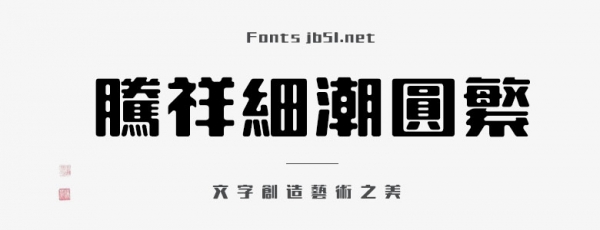
騰祥細(xì)潮圓繁體是一款不錯(cuò)的藝術(shù)字體,由騰祥字庫(kù)出品,字體是在細(xì)潮黑基礎(chǔ)上變換設(shè)計(jì)而成。細(xì)潮圓將細(xì)潮黑的棱角柔化形成被融化之感,融化了的筆畫(huà)圓潤(rùn)富于親和力,適合應(yīng)用于藝術(shù)設(shè)計(jì)、平面宣傳設(shè)計(jì)、網(wǎng)頁(yè)設(shè)計(jì),書(shū)法字帖等領(lǐng)域,需要的朋友可以前來(lái)本站下載。
騰祥細(xì)潮圓字體是在細(xì)潮黑基礎(chǔ)上變換設(shè)計(jì)而成。細(xì)潮圓將細(xì)潮黑的棱角柔化形成被融化之感,融化了的筆畫(huà)圓潤(rùn)富于親和力。字形結(jié)構(gòu)扁方、端莊,橫豎筆畫(huà)粗細(xì)比例適度、豎筆粗壯有力,布白均勻、行文貫通。細(xì)潮圓筆畫(huà)簡(jiǎn)潔圓潤(rùn)細(xì)微處變換靈動(dòng),即實(shí)用又富有裝飾效果,且清晰易讀。適合標(biāo)題和屏顯用字,可用于印刷出版、包裝設(shè)計(jì)、廣告設(shè)計(jì)、網(wǎng)頁(yè)設(shè)計(jì)、屏幕顯示等。